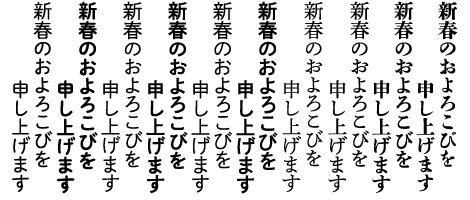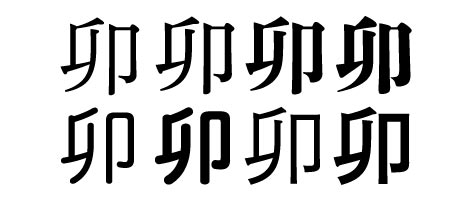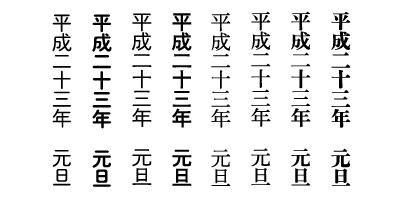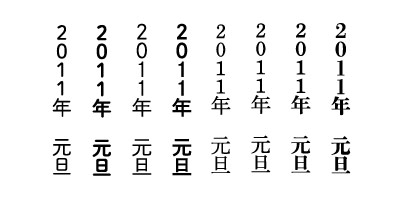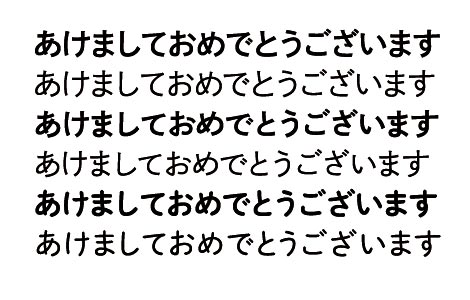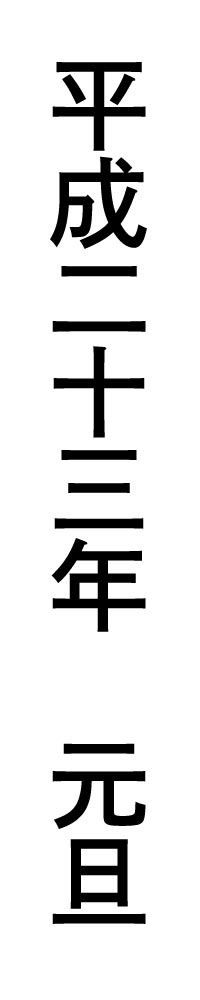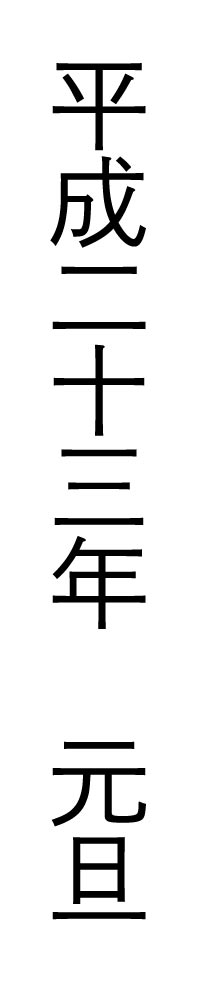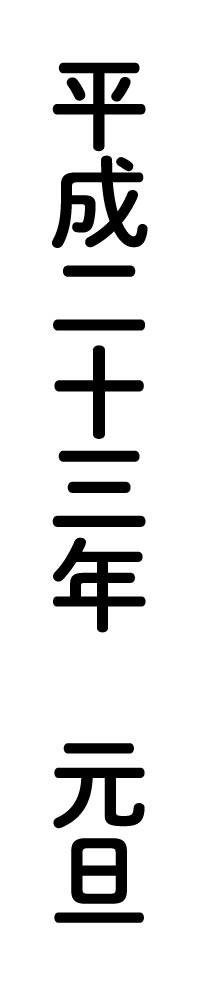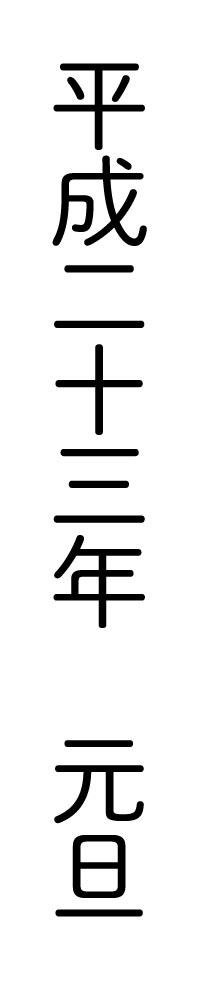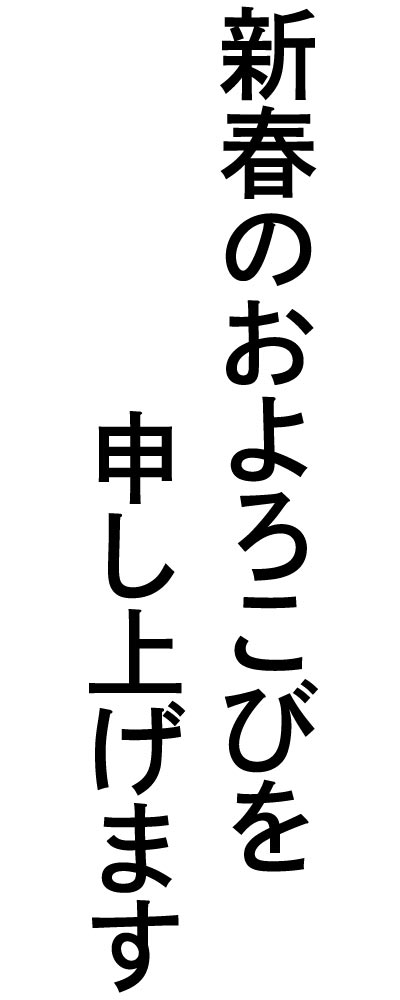
第31回 2010年は勢揃いした改刻版秀英体で年賀状を作ろう!
暑い暑いとこの間まで言っていたのに街はクリスマス一色、もう師走です。今年も秀英体で年賀状はいかがでしょうか。
今回の(というか今年初の……)秀英体のコネタは、一年間のご愛顧に感謝いたしまして、秀英体で年賀状文例をご用意しました。
ついに!秀英角ゴシック丸ゴシックの太いウエイトも年賀状に登場です。これで明朝系ゴシック系あわせて10書体の平成の大改刻ファミリーのおひろめです。来年の干支であるうさぎのように、2011年が皆様にとって飛躍の年となるよう、年賀状をいろどります。
定番のご挨拶
これがなくてははじまらない、年賀状定番の挨拶です。昨年は開発中だった、角ゴシックと丸ゴシックの太いウエイトでもご用意しました。絵柄や写真とあわせて配置しても、力強く印象的な年始の挨拶になりますよ。
右から
秀英体は漢字も気合いを入れて作っていますので、ぜひ漢字仮名交じりの賀詞もおすすめです。
右から
来年の干支は……卯!
来年の干支は「卯」ですので、この一文字をバーンと大きく使いたいですよね。
個性様々な秀英体を試して、お気に入りの「卯」を見つけてください。
やはりオススメは初号! 秀英初号特有の「どこまで下がるんだ!」という位置にあるハネをご堪能ください。
※角ゴシックA・Bは、漢字は共通のデザインですので1種類です。
上段右から
下段右から
忘れちゃいけない、元旦!
細かいところまで秀英体を使って、他の年賀状とは差をつけちゃいましょう!
年賀状に記す年と元旦、こちらも秀英体です。
※角ゴシックA・Bは、漢字・数字は共通のデザインですので1種類です。
右から
秀英明朝M →高解像度画像はこちら
秀英明朝L →高解像度画像はこちら
秀英角ゴシック(A・B共通)B →高解像度画像はこちら
秀英角ゴシック(A・B共通)L →高解像度画像はこちら
秀英丸ゴシックB →高解像度画像はこちら
秀英丸ゴシックL →高解像度画像はこちら
右から
秀英初号明朝 →高解像度画像はこちら
秀英明朝B →高解像度画像はこちら
秀英明朝M →高解像度画像はこちら
秀英明朝L →高解像度画像はこちら
秀英角ゴシック(A・B共通)B →高解像度画像はこちら
秀英角ゴシック(A・B共通)L →高解像度画像はこちら
秀英丸ゴシックB →高解像度画像はこちら
秀英丸ゴシックL →高解像度画像はこちら
角ゴ丸ゴで横組年賀状も作っちゃおう!
横組の年賀状もたくさんありますよね。POPな年賀状に似合うよう、角ゴシックと丸ゴシックで、横組のご挨拶も作ってみました。
上から
秀英角ゴシック(Aタイプ)B →高解像度画像はこちら
秀英角ゴシック(Aタイプ)L →高解像度画像はこちら
秀英角ゴシック(Bタイプ)B →高解像度画像はこちら
秀英角ゴシック(Bタイプ)L →高解像度画像はこちら
秀英丸ゴシックB →高解像度画像はこちら
秀英丸ゴシックL →高解像度画像はこちら
あっという間の2010年、さまざまなかたちで秀英体をご紹介することができました。
昨年11月に秀英明朝LがMORISAWA PASSPORTに追加されて以来、書籍に雑誌にと少しずつ秀英体を見かける機会が増えてまいりました。そして今年9月、ファミリーである秀英明朝M・Bと秀英初号明朝が新たに仲間入り。MORISAWA
PASSPORTユーザーの皆様のお手元に届いています。
時間をかけて大切に作ってきた明朝ファミリーですが、これからは皆様のもとで、この4書体が育っていくのを見守る段階になりました。他の明朝体にはない強い個性のある4書体、きっとお役に立てるシーンがあるはずです。どうぞよろしくお願い致します。
また、角ゴシック丸ゴシックのファミリーは、開発が佳境です! 字母が揃ってきて、チエックと修正を繰り返しています。製品化にはもう少しお時間を頂きますが、どうぞ楽しみにお待ちください!
テレビドラマや映画になった「BUNGO -日本文学シネマ-」の字幕になったり、「タクティクスオウガ 運命の輪」に採用頂いたり、メディアタブレット「GALAPAGOS」に搭載頂いたり、古い活字見本帳をiPhoneやiPadで配信したり、と、そしていろいろな電子書籍のビューワーで本文用書体として皆様のお手元に届いたりと、印刷以外での利用もぐっと増えた一年でした。
そしてそして、年が明けても秀英体! gggでの展覧会「秀英体100」が1/11からスタートします。こちらは東京だけでなく、大阪、福島へと巡回する予定です。超豪華デザイナー陣25組によるオール新作のポスターは、秀英体の新たな魅力が満載。一世紀にわたる秀英体の誕生から平成の大改刻までの流れもぎゅぎゅっと圧縮してご紹介します。関連イベントもたくさんご用意しておりますので、どうぞご参加ください。
それでは2011年もうさぎのように跳ね回る秀英体をよろしくお願い致します。
(2010.12.13 佐々木)